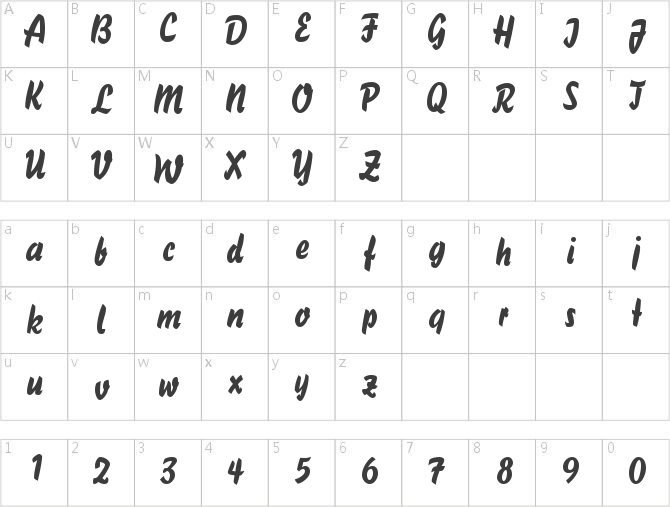
handybrushregular 詳情頁
字體名稱: handybr
handybrushregular
handybrushregular字體字庫是一款讓人賞心悅目、百看不厭的英文字體,適合各類廣告和產品包裝設計應用,字體大小0.05MB,格式為ttf字體,上傳用戶是舒甜咖啡,作者/版權方為未知